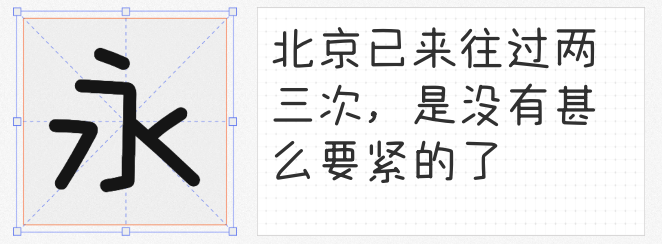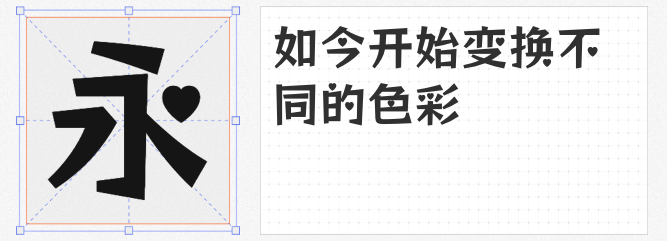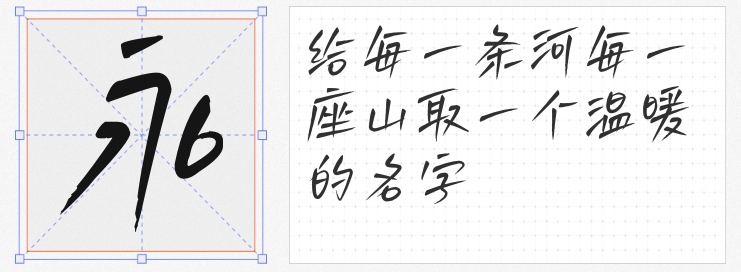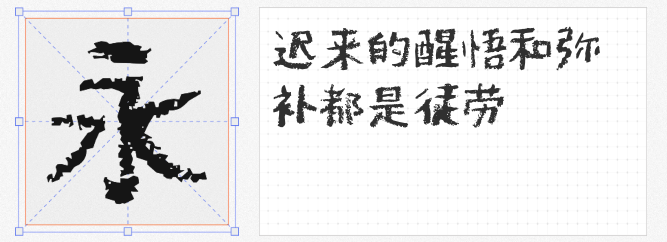
六一儿童节将至,设计师们是否在为如何打造充满童趣的视觉作品而发愁?除了配色和元素,字体的选择同样关键。今天,我们精选了四款风格独特、免费商用的可爱字体,让你的设计瞬间充满活力与天真气息!
这款由山人白路手写的字体,以文艺清新风格脱颖而出。6796个字符涵盖中文、数字、英文及标点,笔画流畅自然,仿佛孩子稚嫩的笔触,又带着一丝书卷气。无论是制作儿童节贺卡、手账模板,还是搭配插画设计,它都能为作品增添一份温暖与治愈感。虽然风格偏文艺,但手写质感与童趣元素结合,让它在儿童节设计中毫不违和。
专为儿童与母婴场景设计的大宝桃桃体,将圆点部件替换为爱心符号,瞬间让文字充满甜美感。字形圆润饱满,笔画间距宽松,自带“萌萌哒”滤镜。无论是标题设计、海报标语,还是绘本正文排版,这款字体都能轻松营造无拘无束的童真氛围。即便作为正文字体,它的可爱感也不会显得突兀,反而能提升阅读的趣味性。
如其名,字帮玩酷体以“玩”为核心设计理念。字形错落有致,笔画多元且富有动感,20923个汉字与987个符号覆盖全场景需求。它的风格介于童趣与潮流之间,既适合儿童节活动主视觉设计,也能驾驭萌系IP周边产品。用这款字体搭配夸张的插画或动态效果,瞬间让画面“活”起来!
这款手写体以蜡笔/油漆涂抹的斑驳质感为特色,墨迹厚重却不显杂乱,反而透出一种粗粝的温柔。它像极了孩子随手涂鸦的痕迹,自带岁月感却不显沧桑,非常适合动漫标题、诗歌短文或怀旧风格海报。在儿童节设计中,它能与其他卡通元素形成反差萌,为作品注入文艺气质。
四款字体各具特色。无论是需要温馨手写感、甜美爱心风,还是活泼玩趣或文艺涂鸦风,它们都能完美适配六一儿童节设计需求。更难得的是,这些字体均支持免费商用,设计师们可放心使用!